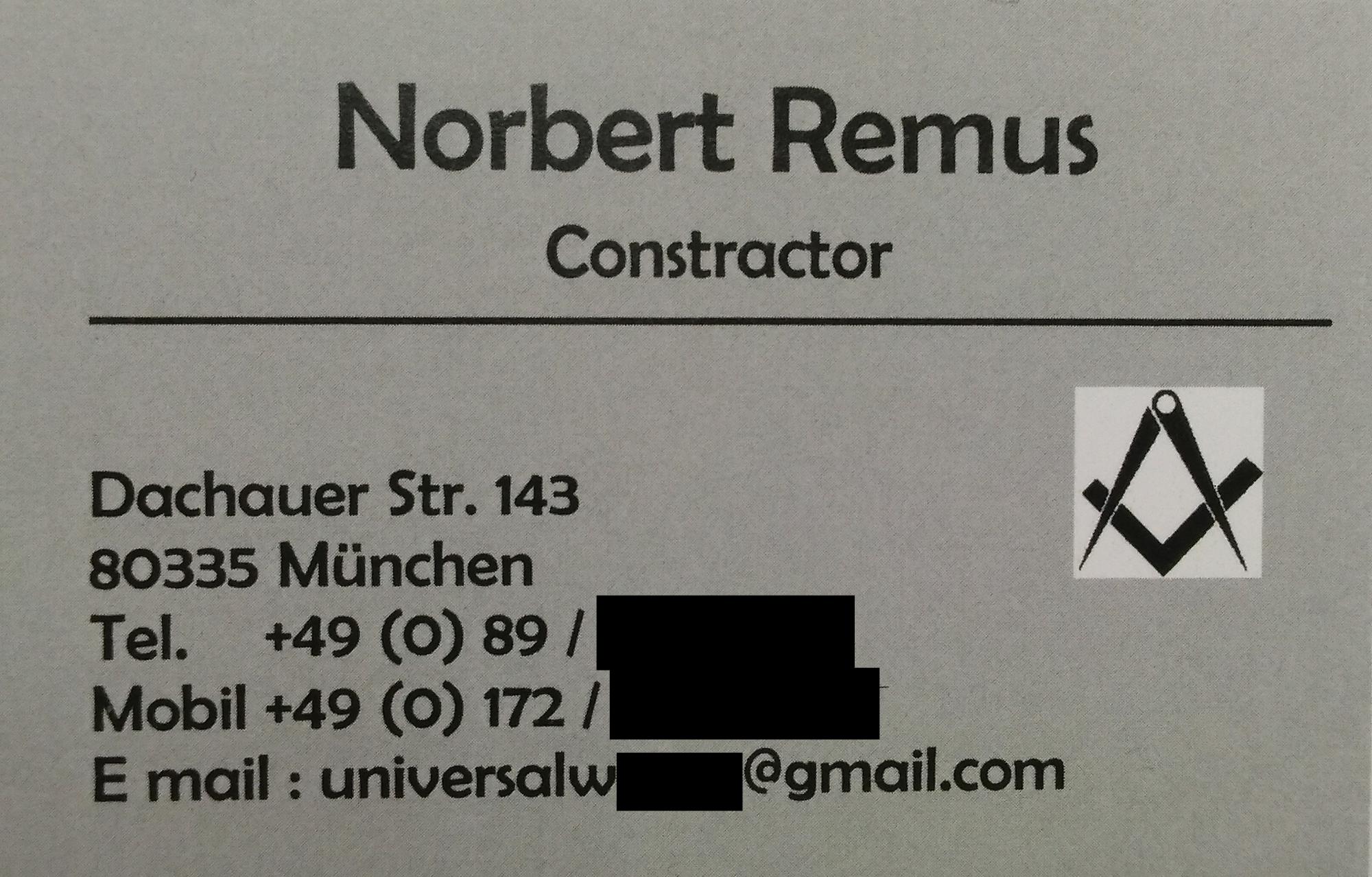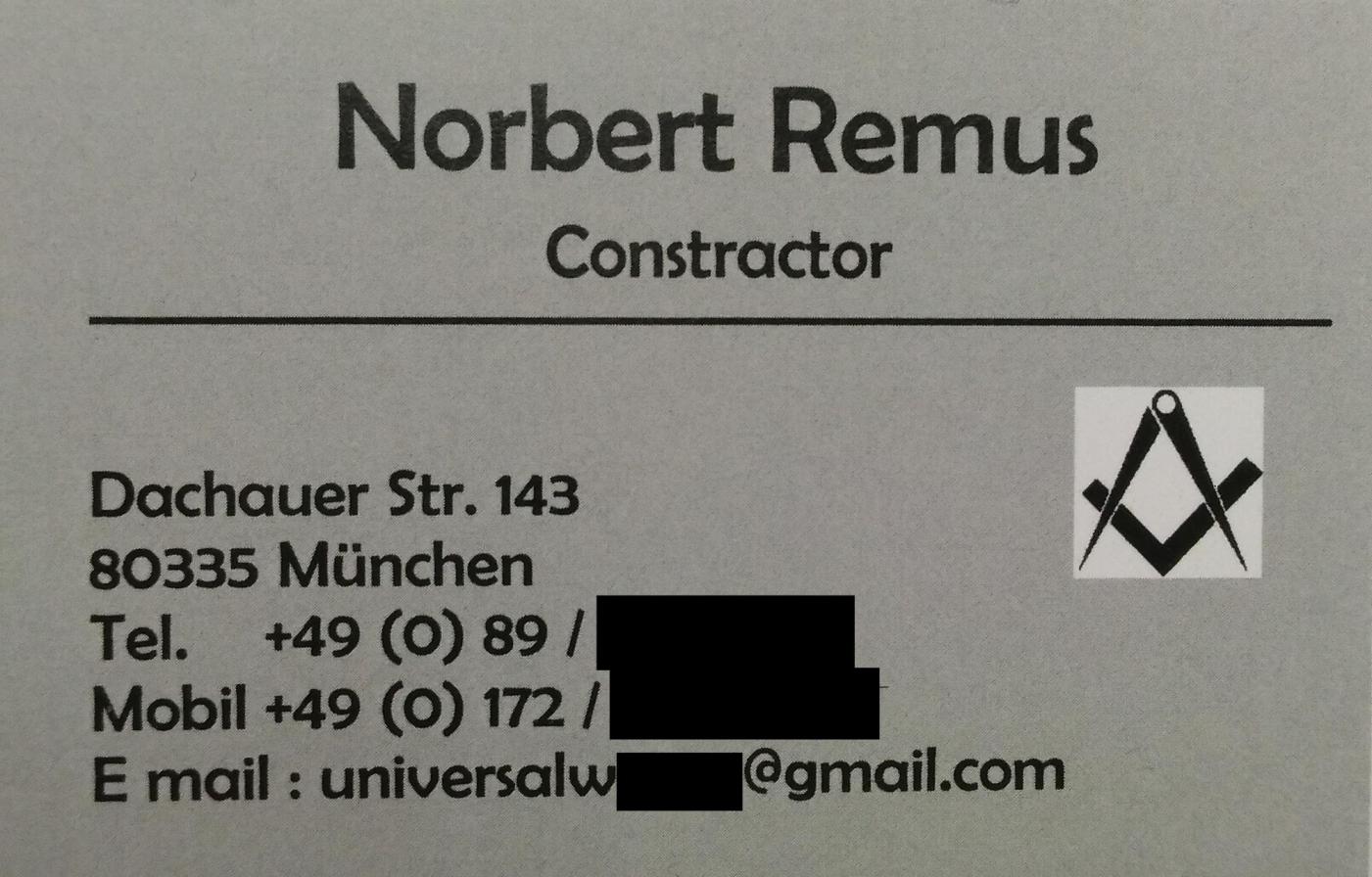
Suche Schrift von älterer Visitenkarte Remus
ich suche mal wieder verzweifelt eine Schrift.
Herr Remus hat mir einfach nur die Visitenkarte hingeklatscht und gesagt...genau SO.
Nun soll ich sie quasi nachbauen, aber ich finde keine nur annähernd passende Schrift.
Alter der Erstellung der Visitenkarte leider unbekannt.
Der Hintergrund war gerastert, aber ich habe es so gut es geht entfernt.
Schade... ich finde auch gar nichts, was da irgendwie auch nur in die Nähe kommt...
Es müsste eigentlich »Constructor = Konstrukteur / Erbauer« heißen.
“Contractor” = »Bauunternehmer« oder aber »Maurer« – passend zu den abgebildeten Werkzeugen Zirkel und Winkelmaß.
meiner Erfahrung nach sehen die Kunden selten Unterschiede in der Schrift (ich hätte da einfach die Futura genommen), aber falsche Schreibweisen (wie z. B. falsch geschriebene Straßen) wollen die partout behalten...